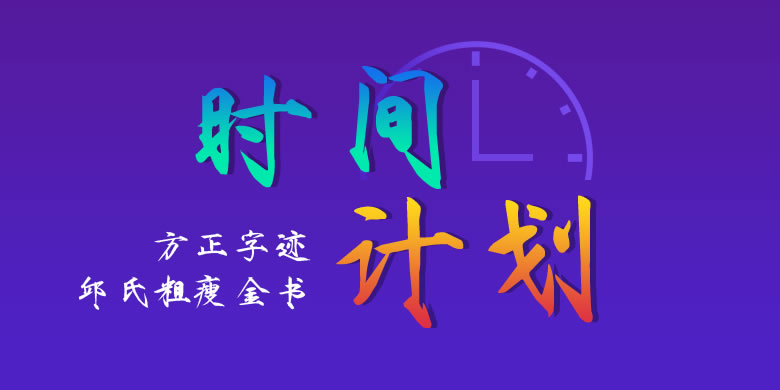
方正字迹-邱氏粗瘦金书
字体品牌: 方正字迹 设计师: 邱金生 字体分类: 常规书写·毛笔 字体属性: 精品字 字符集: 大陆简体(GB2312-80) 发布时间: 2011
方正字迹-邱氏粗瘦金书由邱金生先生创作。瘦金书本来偏“瘦”,在实际版面中易虚化而不易远观,这款字体加粗了笔画,笔形和结构高度稳定,易读性强。其风格雍容高雅,适用于文化类的宣传设计,以及商业类品牌的广告和产品包装设计。